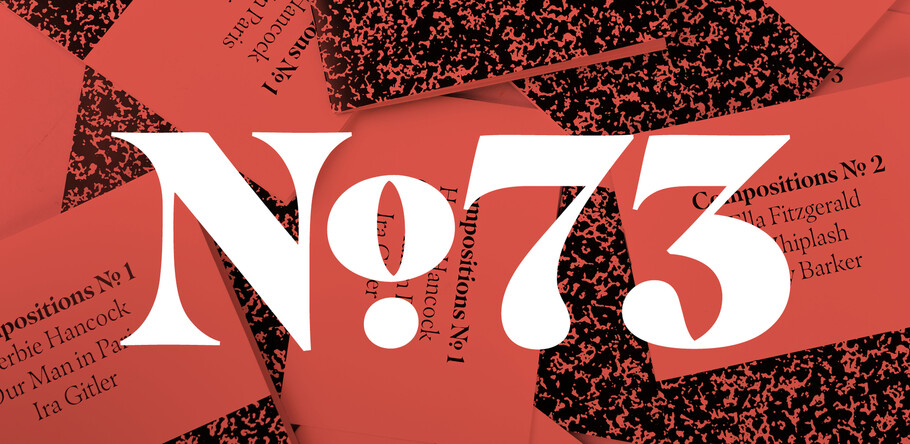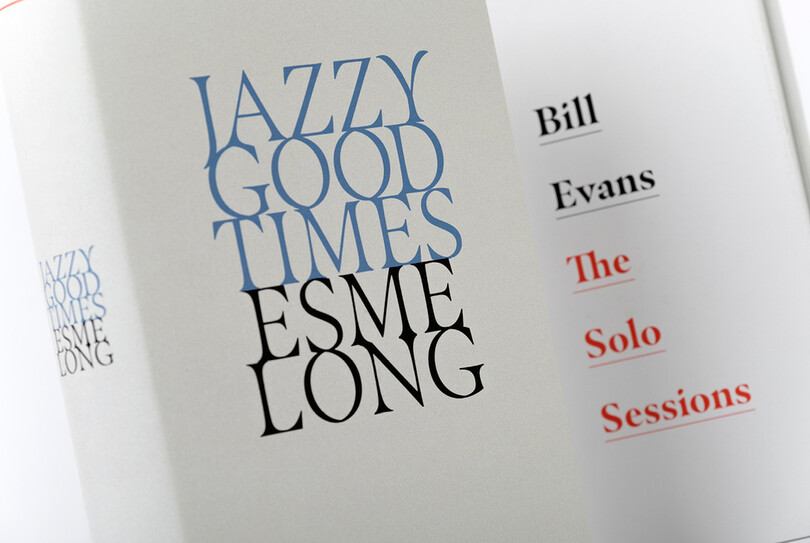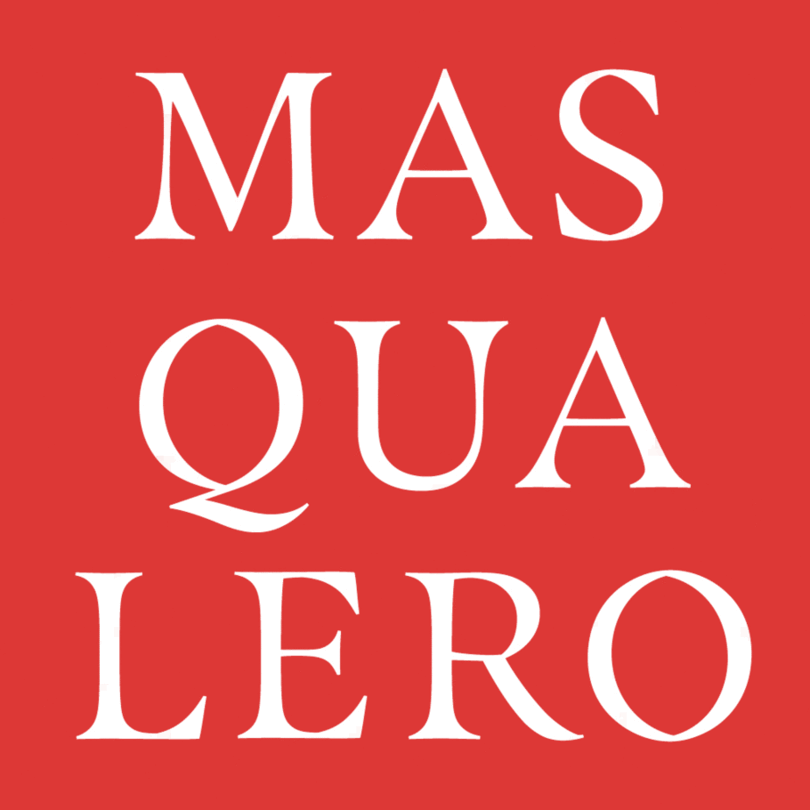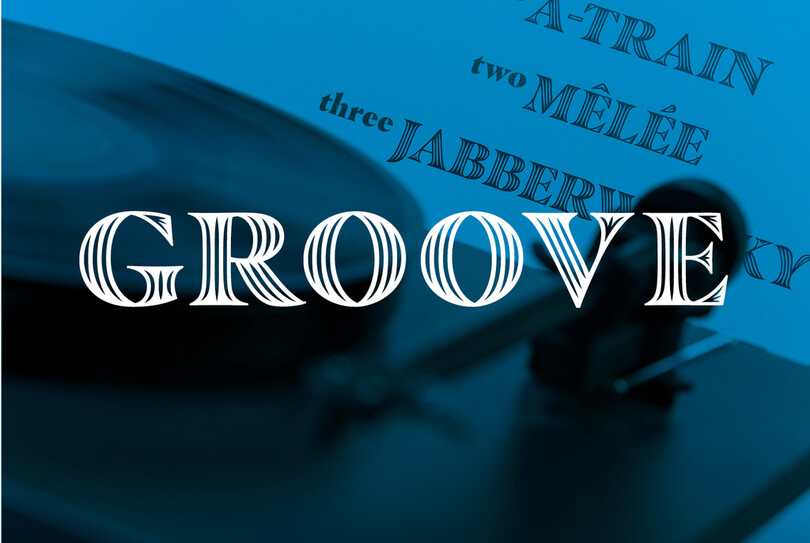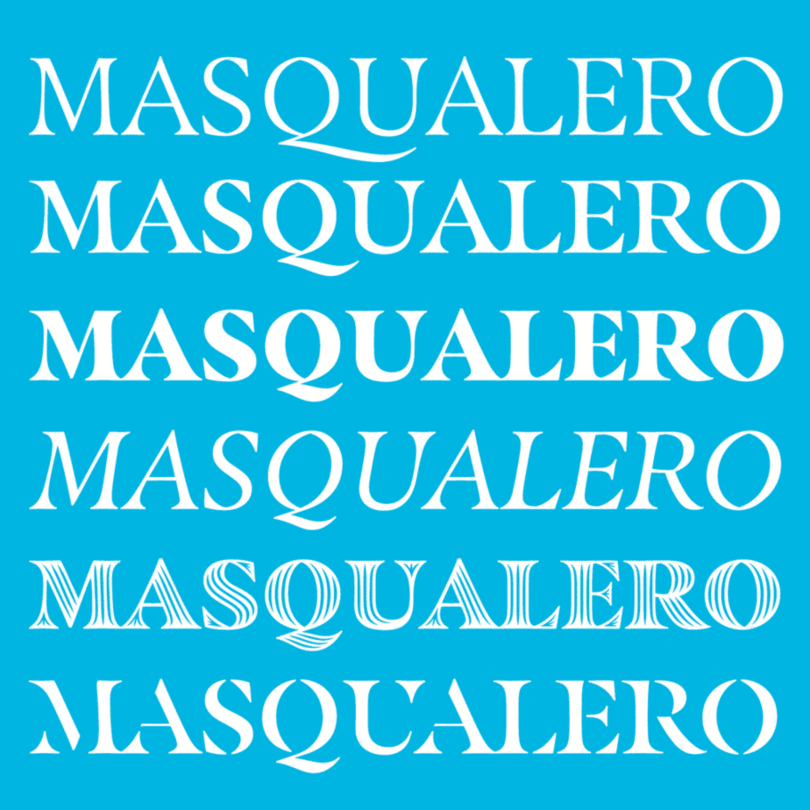
シャープで高級感溢れるセリフフォントMasqualero
Jim Fordが制作したMasqualeroは、アメリカのジャズミュージシャンであるMiles Davis(マイルス・デイヴィス)にちなんで名付けられただけでなく、マイルスの際立つ個性を、そのシャープなセリフの最後の1つに至るまで再現しています。勢いのある文字に、多くの複雑なディテール。この書体は、使用するデザイナーの手や書体に込められる言葉に応じて、暗かったり、明るかったり、歓迎されたり、脅されているような印象を受けます。6種類のウエイトとイタリック体を備えているこの書体のカスタムメイドの文字はそれぞれ、読み手を捉えて離さない魅力的なデザインで構成されています。
Masqualeroの書体デザイナーFordが吹雪の中、車でMiles Davisの同名の曲を聴いたときに突然思いつき、長い道のりでこの歌を繰り返し聞き、書体の初期のディテールを頭の中で形作しました。家に戻るなり、Masqualeroという10文字をスケッチし始め、全体のデザインの基礎を形成しました。
「私はこの名前を気に入っています。語呂が良く、深い意味をもつものでもないからです」と彼は説明しています。「Masqualero」というのは、Wayne Shorter(ウェイン・ショーター)がバンドにいた時に思いついた抽象的な言葉です。つまり、Masqualeroは常にその世界とその歌そのものを意味しています。
「Miles Davisのキャリアと個性を醸し出すこの書体には、多くのディテールがあります」と彼は付け加えています。「Miles Davisは言葉が辛辣で、とても頑固な人物でした。多くの人が彼に近寄りがたいと考えていたと思います」
気難しい個性を持つミュージシャンにちなんで名付けられたMasqualero は、デザインの開発においてもMiles Davisの個性が忠実に再現されており、それぞれの文字の複雑なディテールの作成には困難を極めました。
Masqualeroの大胆な個性は出版の世界にぴったりです
Matthew Carter(マシュー・カーター)の作品を参考にしているデザイナーFordは「Masqualeroには見たことのない、また思いもしなかったような、先端の装飾がたくさんあります」と、述べています。「しかし、それこそが本当に鮮やかな輝きをもたらしているのです。Masqualeroはすべて彫り刻まれたものであり、それぞれの文字がユニークです」
文字のシャープなラインを作り出すために、Fordは石切りの世界からヒントを得て、各文字の要素間には特に美しいつながりを作り出しています。彼は、各グリフに対して、あたかも「大理石の彫刻」を切り出すかのようなアプローチを取り、1文字ずつ取り組み、コピーと貼り付けに頼ることを拒みました。
このような手法は、デザインの変わり続ける個性とは対照的に、従来の価値観や伝統といった感覚を呼び起こします。その二面性により、このフォントをどのように使用するかに応じて、近寄りがたく、あるいは洗練された、またはその間にあるあらゆるものを同等に表現することができるため、印象が大きく変わる可能性があります。 このフォントの個性は、さまざまなウエイトによってさらに強調されています。そのユニークな性質は、書体の装飾性と妥協のない鮮明さの両方を備えるステンシル体で特に注目を集めています。
このフォントの個性は、さまざまなウエイトによってさらに強調されています。そのユニークな性質は、書体の装飾性と妥協のない鮮明さの両方を備えるステンシル体で特に注目を集めています。
Masqualeroフォントファミリーには、2つの表示ウェイト、ステンシルとグルーブが含まれています。
また、古典的でエレガントなリガチャー、境界線のつなぎ方、そしてDavis自身の手をモデルとした「秘密の」プリンターズフィスト(指示マーク)など、はじめて目にするもの以上のものを提供しています。
Masqualeroは大胆で個性的であり、出版界にうってつけです。Fordは細かく彫刻されたディテールの最適な用途として、雑誌の題字、ロゴ、ブックカバーを提案しています。その重厚なセリフは、建築用の看板、あるいは生活上のより細々したものにブランドを記すのにも適しています。
「ファッション記事向けといえるほど“メインストリーム”のフォントファミリーというわけではありません。これは黒いタキシードか細くとがったヒールです。このフォントが言葉をドレスアップするのです」